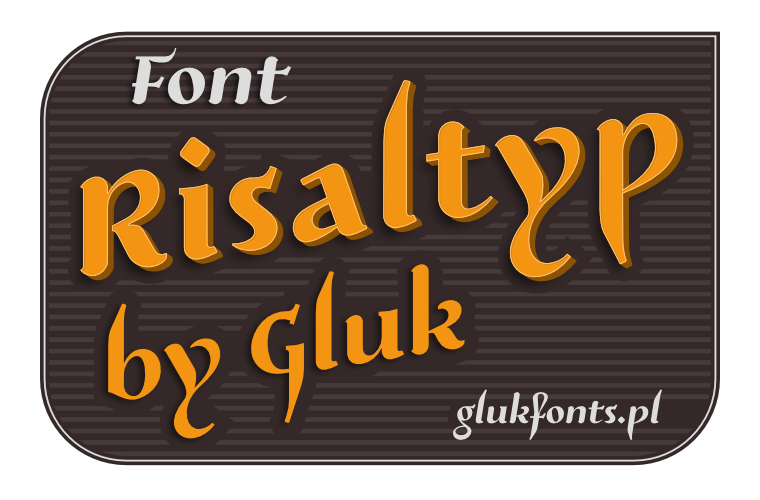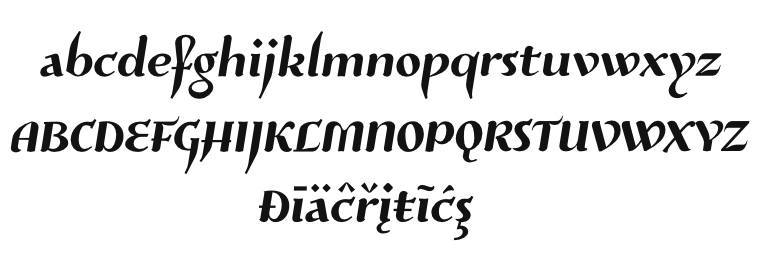
Dekoracyjny, pochyły font Risaltyp. z alternatywami kontekstowymi, ligaturami i zestawem stylistycznym S01 (alternatywne e). Dodatkowo dostępny font RisaltypS01 z domyślnie wstawionymi znakami z zestawu stylistycznego S01.
- font: Risaltyp